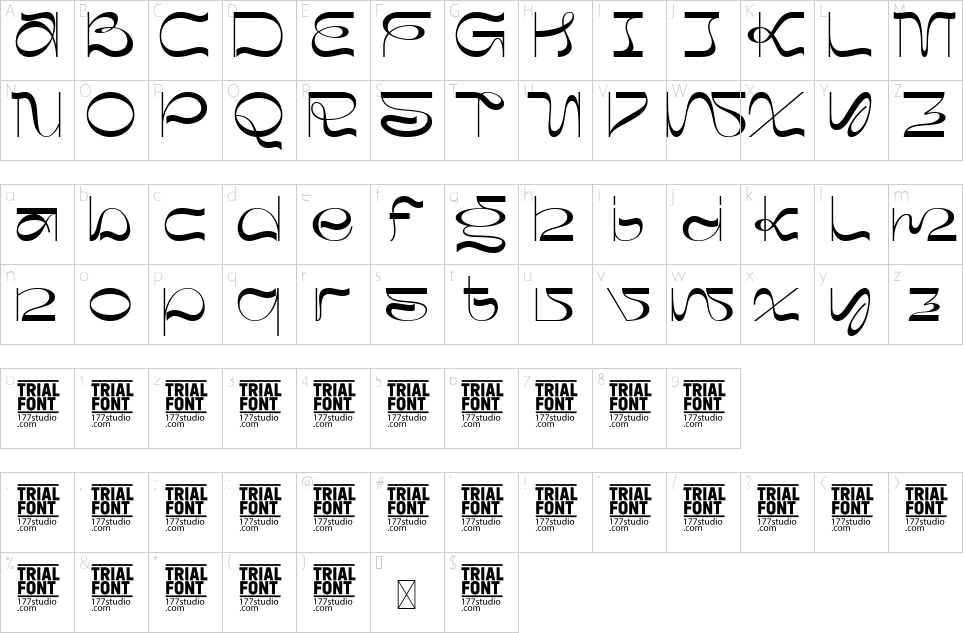
Descubra a elegância e a modernidade da fonte James Digital, uma opção gratuita e incrivelmente completa para seu próximo projeto. Desenvolvida por 177studio.com, esta fonte digital foi projetada para oferecer uma experiência de escrita fluida e sofisticada. Desenvolvida para uso tanto em sistemas Windows quanto Mac, James Digital foi descarregada 155 vezes, atestando seu valor e popularidade. Descubra por si mesmo o poder desta fonte, uma seleção exclusiva do James Digital Font | 1001 Free Fonts.